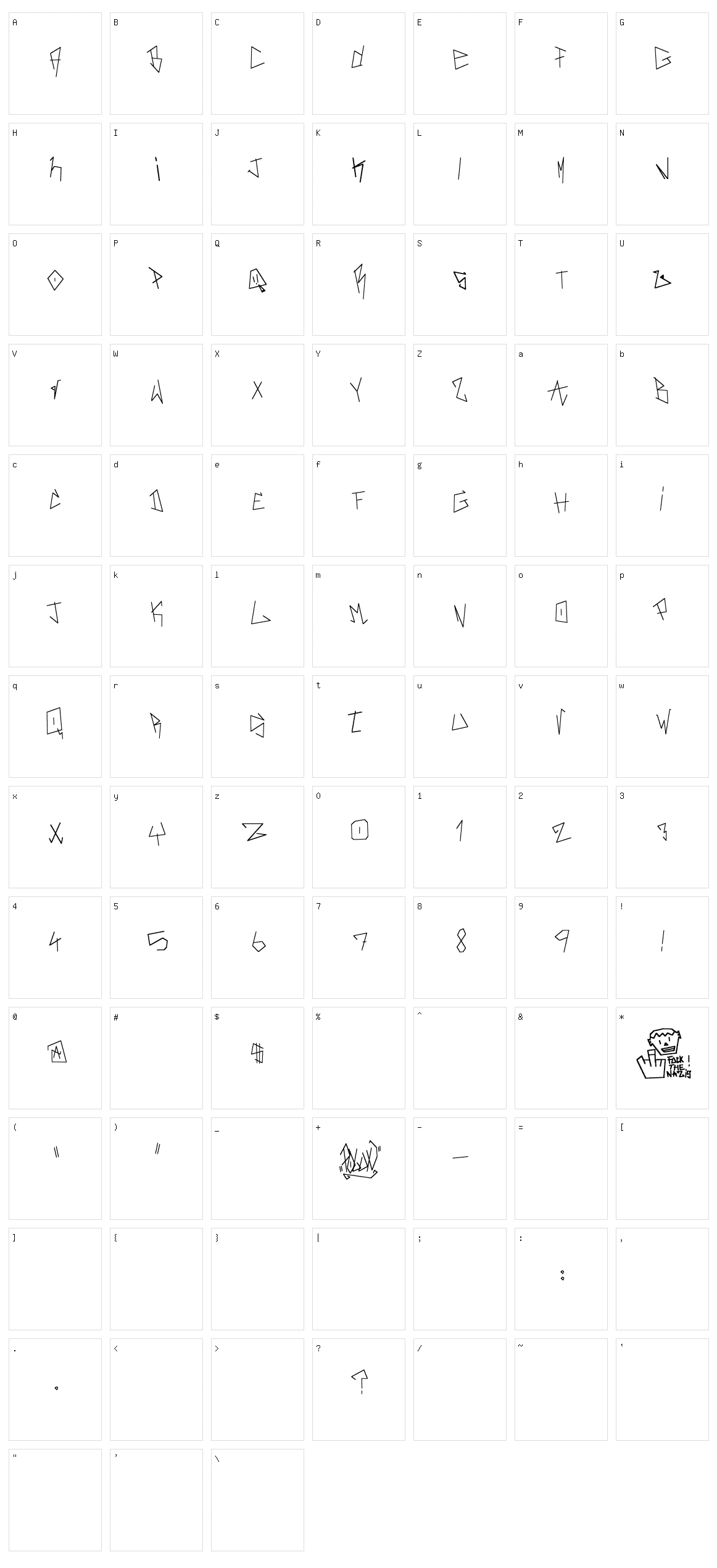
/ <<< REAL BREAKERZ >>> \
Real Breakerz est une police de caractère imitant les célèbres ( à la SNCF ou à la RATP ;-) ) taggeurs qui utilisent cutters , couteaux , ciseaux , lame de rasoirs etc pour laisser une traçe INDéLéBILE de leur passage .... ;-)